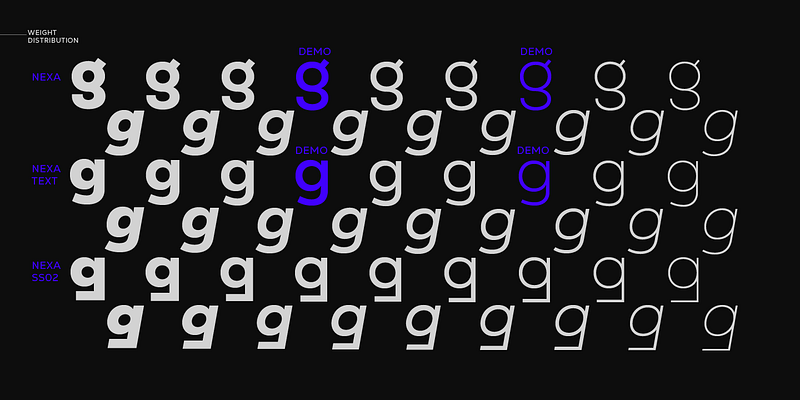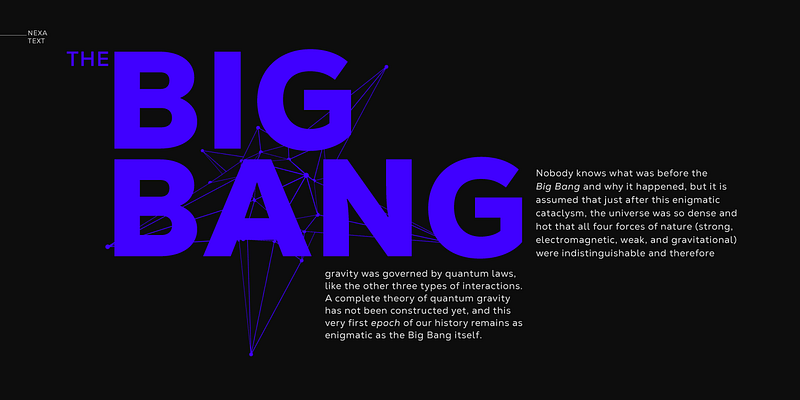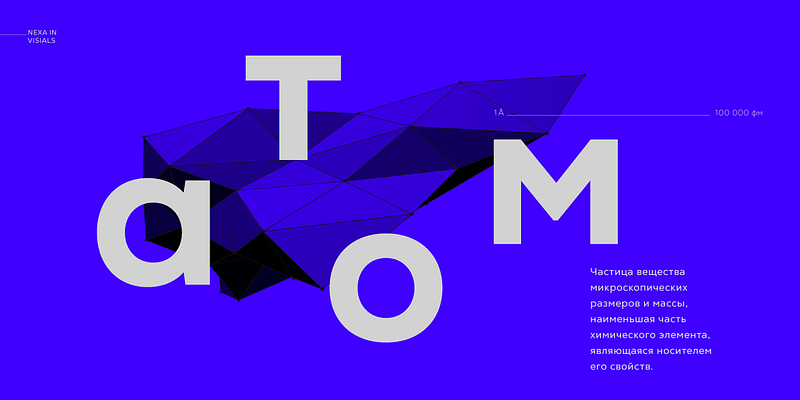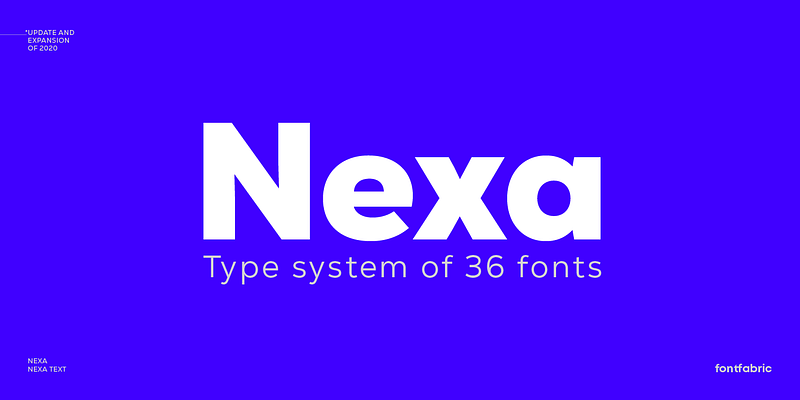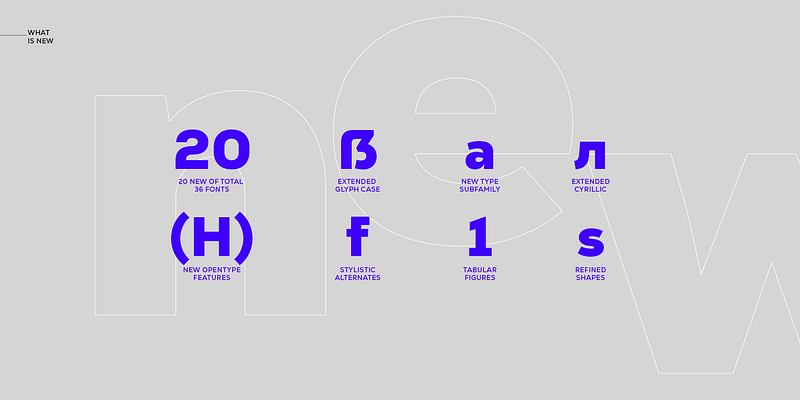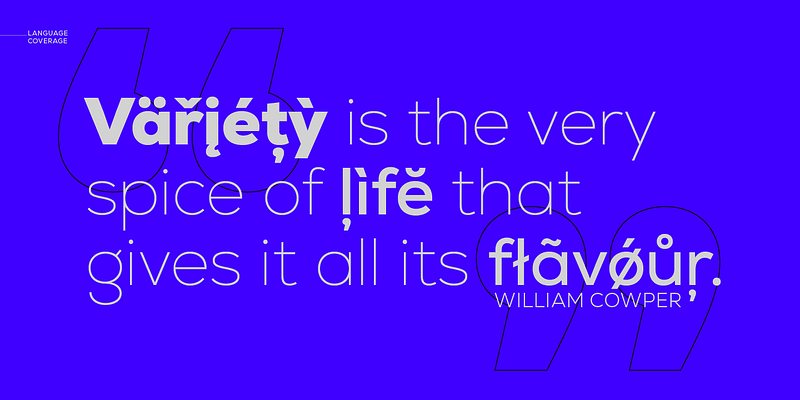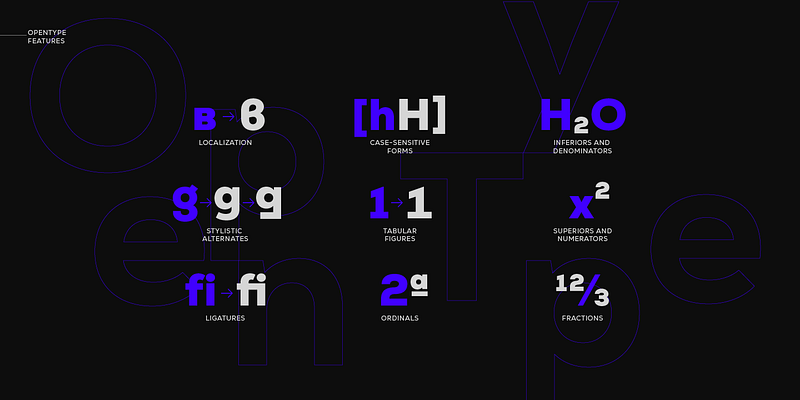
Versión actualizada con mejor kerning de la versión de 2020. Novedades: compatibilidad con idiomas cirílicos; localización al búlgaro; subfamilia completamente nueva, Nexa Text; nuevo grosor ultraligero con su cursiva correspondiente; conjunto estilístico idóneo para títulos y carteles, ss02; cifras tabulares. Incluso las tipografías más reconocidas de la época, como Nexa, deben actualizarse de vez en cuando. Nos enorgullece presentar la última versión actualizada de esta famosa fuente sans serif geométrica. Esta familia de diseños, completamente refinada, incluye un grosor adicional (ultraligero) y su versión cursiva correspondiente, así como una subfamilia totalmente nueva (Nexa Text, optimizada para textos más largos) e incluso un conjunto estilístico de Nexa futurista para ofrecer un aspecto alternativo de cara a títulos y carteles. El resultado es un conjunto de 9 grosores y 36 fuentes. Los glifos que ofrece ahora son compatibles no solo con el latín ampliado y mejorado, sino también con un grupo para cirílico, con la localización de idiomas necesaria. Nexa logra su fluida practicidad gracias a sus múltiples características de OpenType, como las formas que distinguen entre mayúsculas y minúsculas, y alternativas contextuales y estilísticas. La apariencia única de Nexa, sumada a su mucha variedad, la lleva más allá de las tipografías geométricas habituales y la hace adecuada para todo tipo de tamaños y fines, con diseños que hablan por sí mismos.